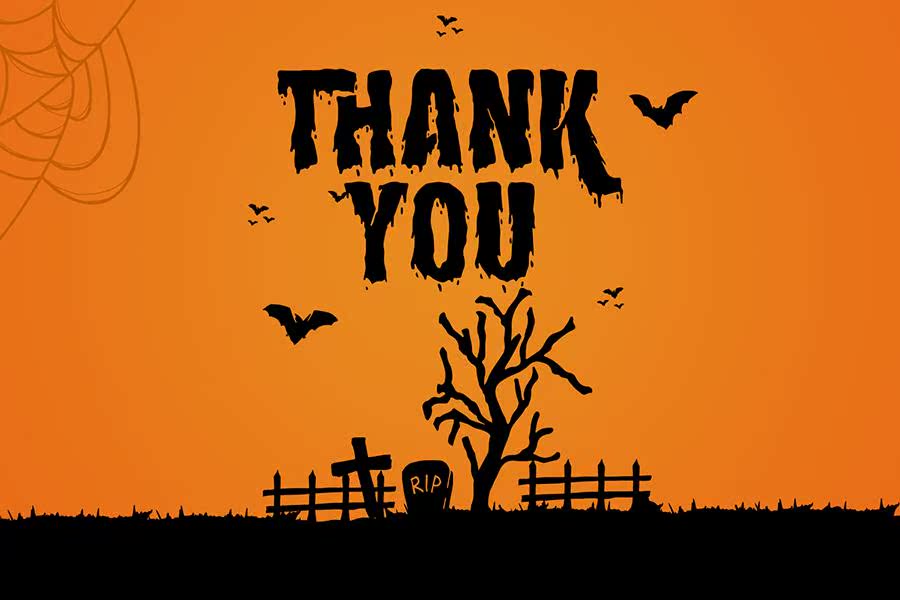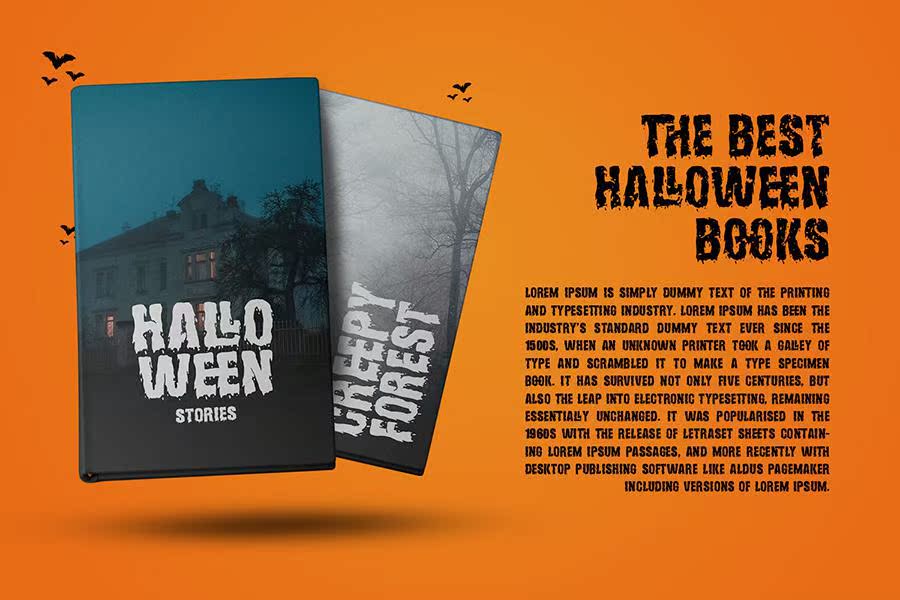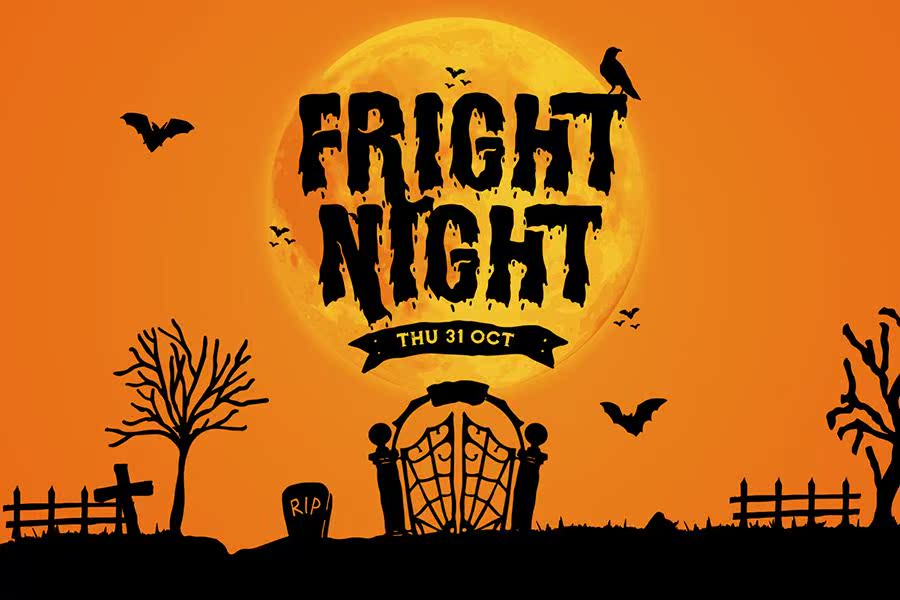
Hollows SpookyDisplayFontSafontCreatedWithrorror和ChickimPression。Hollows有两种不同的风格,常规和粗鲁,每种风格都有不同的可选和连字,使其看起来更具吸引力,更易于使用。Hollows还配有多种语言,可用于各种语言。Hollows为您提供了恐怖和恐怖的环境,使您的万圣节更具吸引力,更适合用于书皮、电影、标识和品牌、广告、海报和其他产品设计。